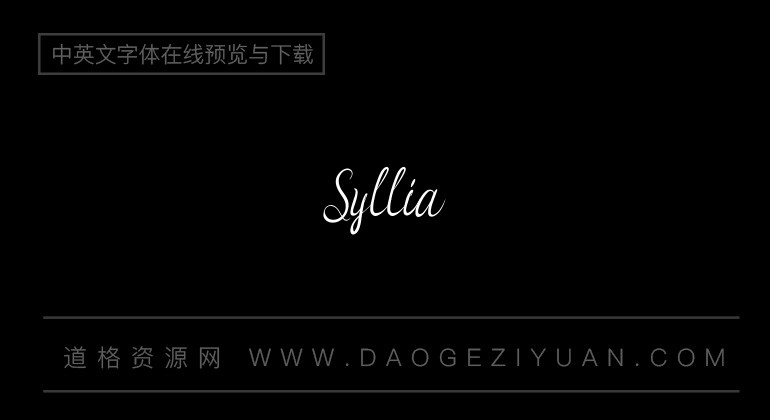
Syllia
Syllia 是一款简约的英文字体,它的特点是拥有细腻的笔画,清晰的线条,以及温柔的曲线。它的字体更加现代,但又不失传统的风格。Syllia 字体可以用于各种设计作品,如海报、图标、标志、标题等,是一款非常适合用于现代设计的字体。
Syllia是一款非常不错的手写艺术字体,具有很好的视觉感,适合于文化类的宣传设计、商业类品牌的广告和产品包装设计以及个性化文字排版等较多场景。